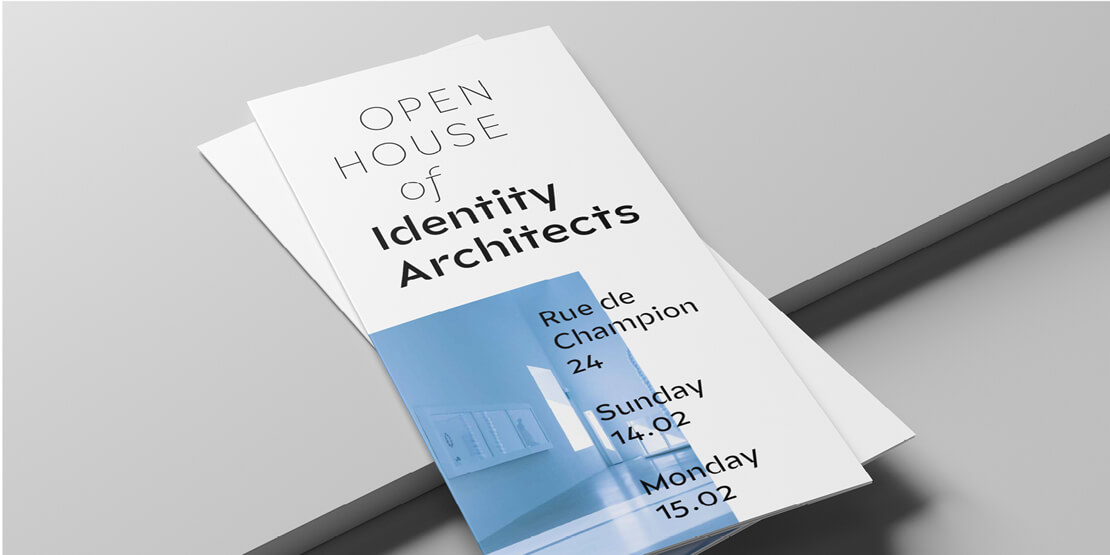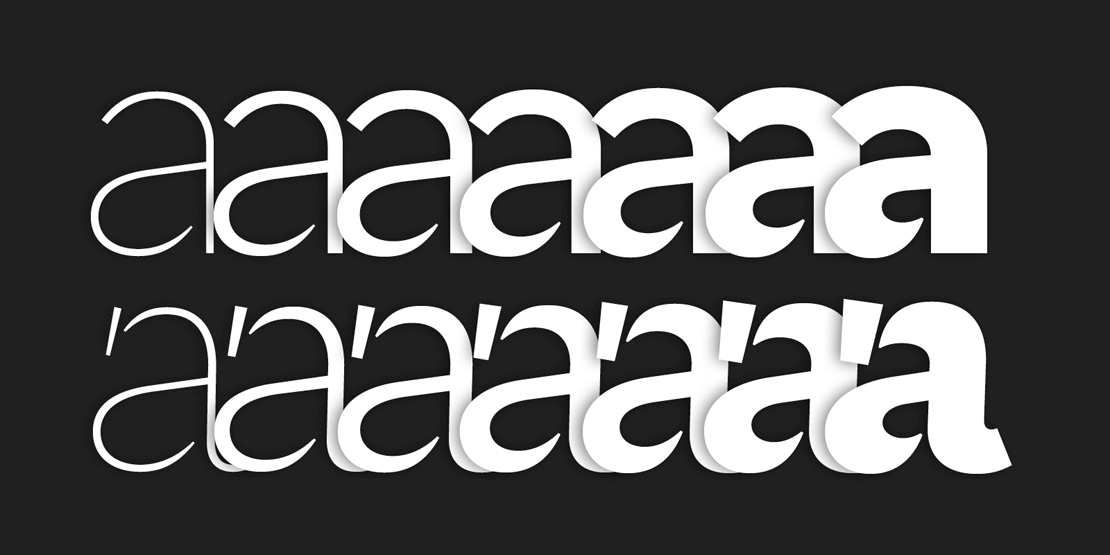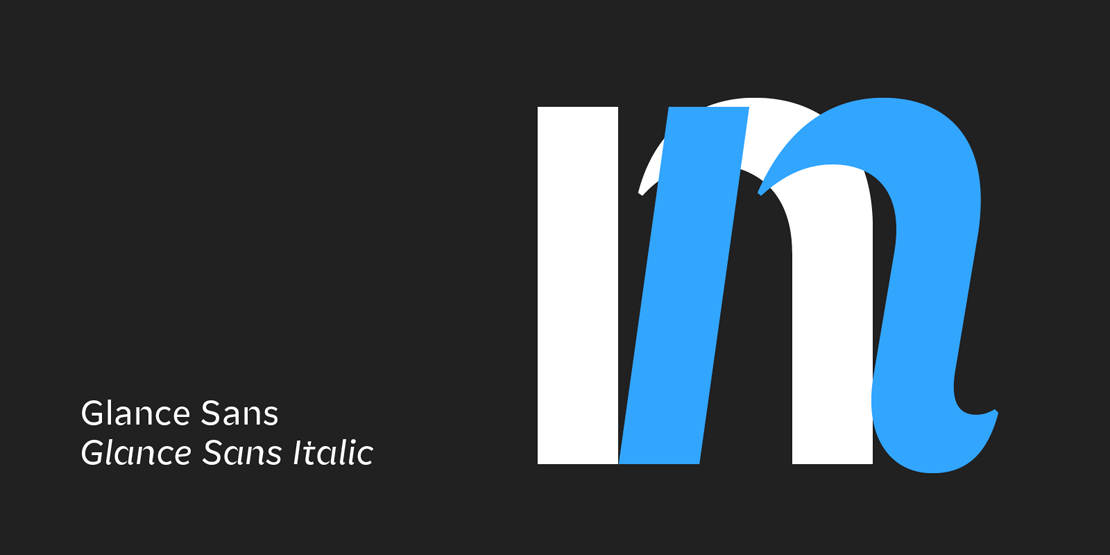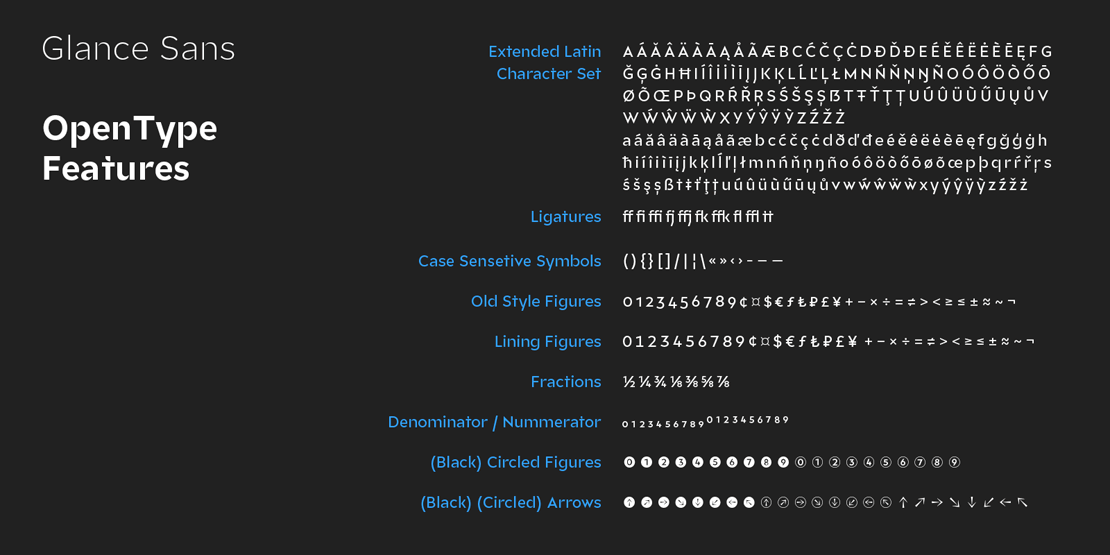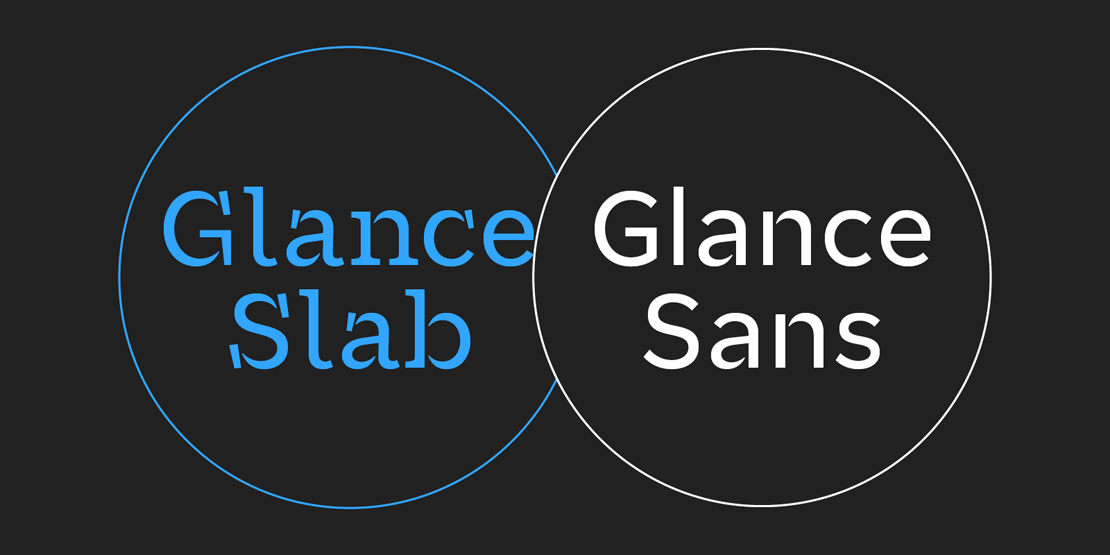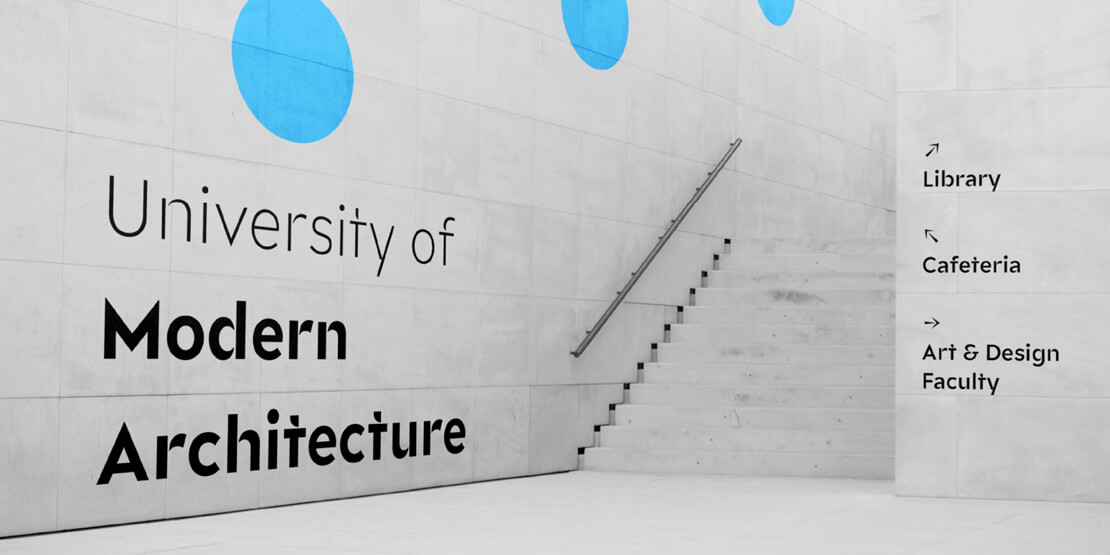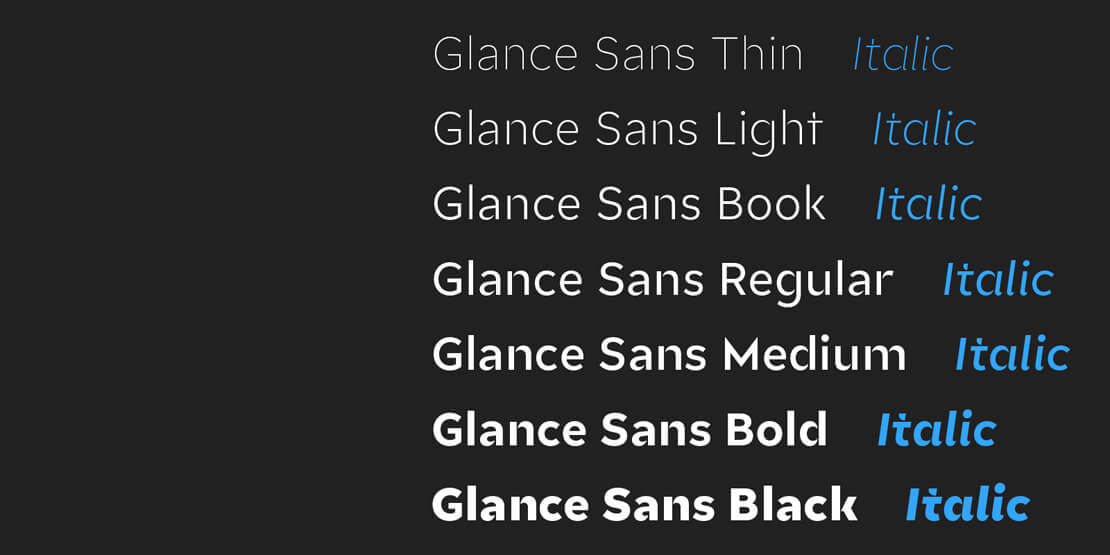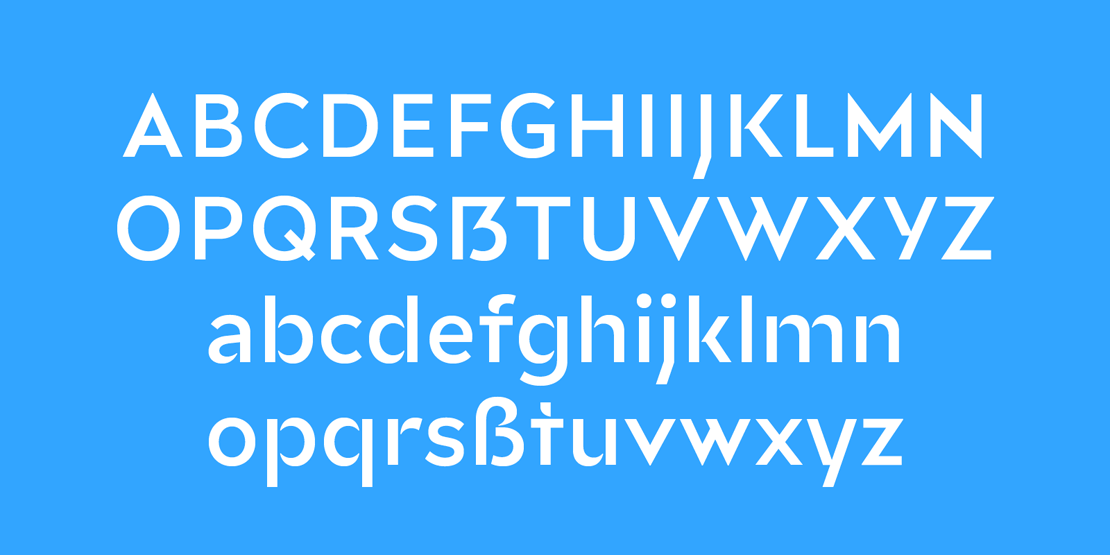
Glance Sans: Eigenwillige Sans-Serif mit Charakter
»Glance Sans« ist eine charaktervolle Sans-Serif von Moritz Kleinsorge. Die Schriftfamilie folgt dem Gestaltungsprinzip der nicht verbundenen Elemente.
Einige Striche der Schriftart verbinden sich nicht mit ihren Buchstabenstämmen, wodurch sichtbare Lücken entstehen und somit ein dynamischer Eindruck von Balance und Bewegung entsteht.
Das Gestaltungsprinzip hatte Moritz Kleinsorge bereits erfolgreich bei der Glance Slab umgesetzt. Die Sans-Serif-Serif wirkt im Gegensatz zu ihrer Schwesterschrift durch das Fehlen der abgesetzten Serifen ruhiger.
»Wenn die Heimat von Glance Slab große, überfüllte Stadien und riesige Sportveranstaltungen sind, bevorzugt Glance Sans Streetball-Plätze, gut genutzte Skateparks und Underground-Clubs.«, so der Designer. »Sie passt sich auch an urbane Arbeitsumgebungen an, von der Finanzbranche bis zum High-Tech-Bereich. Wann immer ein dezenterer Look gefragt ist, ohne die Eleganz eines Athleten zu verlieren, ist Glance Sans einsatzbereit.«
Glance Sans bietet sieben Schnitte sowie einen kompletten Satz Italics. Dabei handelt es sich nicht nur um schräggestellte Variante, sondern um individuell gezeichnete Buchstabenformen, die eher subtil auf die klassische Kursivkonstruktion verweisen, um damit eine effektivere Betonung erzielen zu können.
Unter den mehr als 600 Glyphen der Glance Sans finden sich Extras wie sechs Ziffernsätze, eingekreiste Zahlen, eingekreiste Pfeile und weitere Arten von Währungssymbolen in zwei stilistischen Versionen.